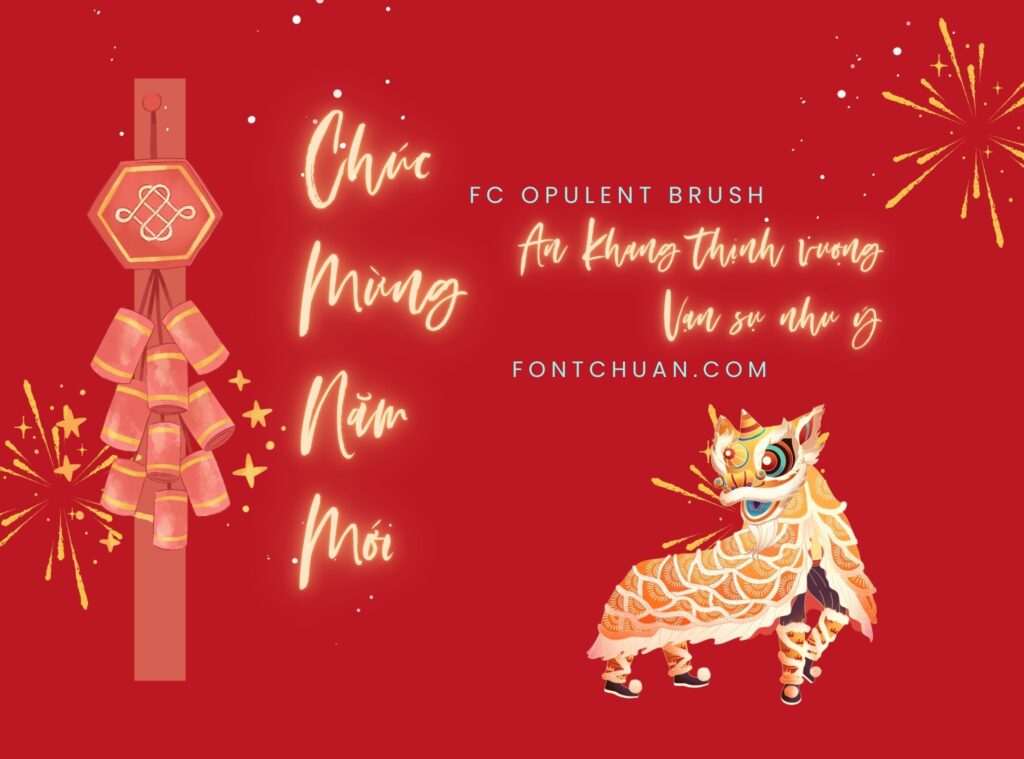
Font FC Opulent Brush Việt Hóa
FC Opulent Brush là phiên bản Việt hóa của phông chữ Opulent Brush, được thiết kế bởi Sam Parrett vào năm 2018. Phông chữ này thuộc loại script với phong cách viết tay hiện đại, ngoài kiểu dáng thư pháp, font này còn mang lại cảm giác sáng tạo và nghệ thuật.
Với thiết kế viết tay hiện đại, phông chữ Opulent Brush phù hợp cho các ứng dụng như thiệp mời, tiêu đề, đặc biệt là các font chữ Tết như lịch Tết, câu chúc mừng năm mới, hoặc các ấn phẩm in ấn cần sự cá nhân hóa. Đồng thời, font này cũng rất thích hợp làm font Nhà giáo Việt Nam, giúp tạo ra các thiết kế thiệp, poster hay banner tri ân giáo viên đầy tinh tế và ấn tượng. Trong lĩnh vực sự kiện, phông chữ này có thể được sử dụng trong các dịp như thiệp cưới, lễ hội và sinh nhật. Ngoài ra, FC Opulent Brush cũng thích hợp cho các ngành nghề như quảng cáo, spa và ẩm thực.